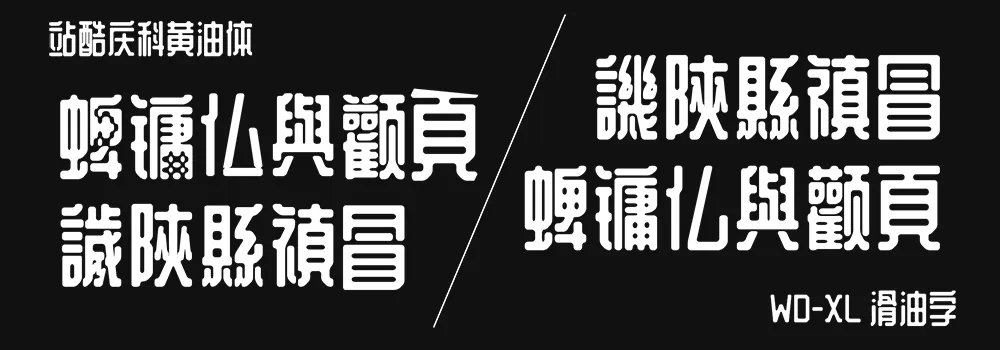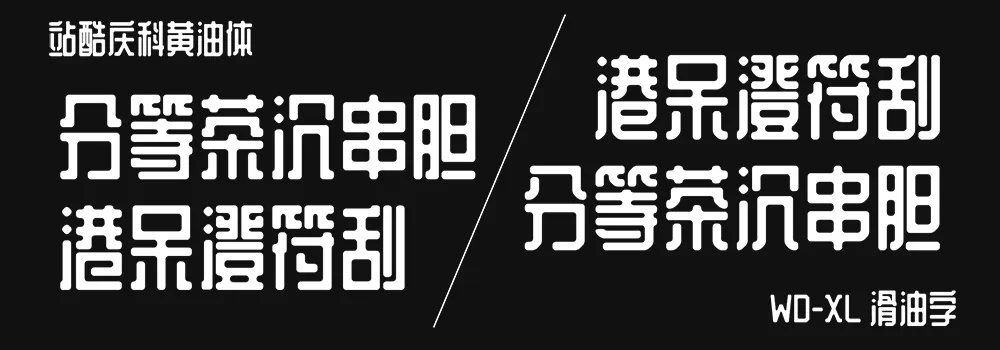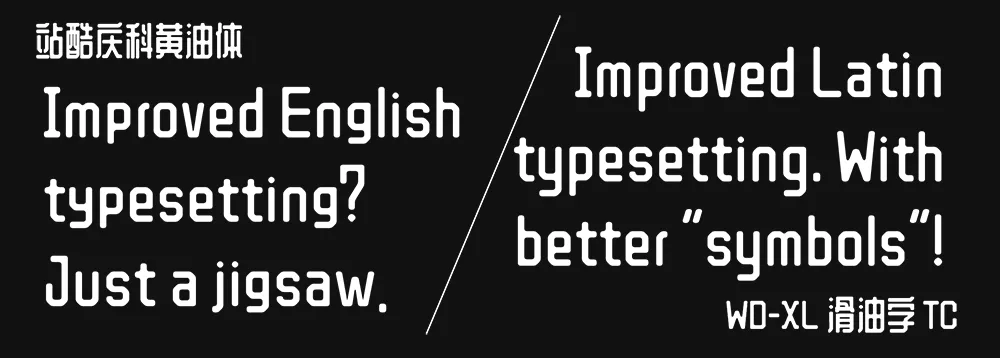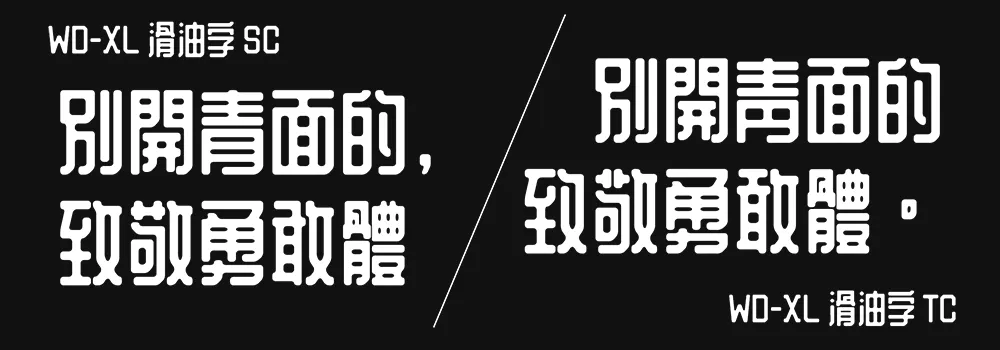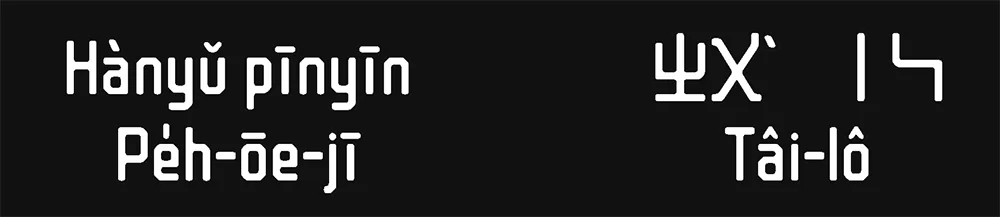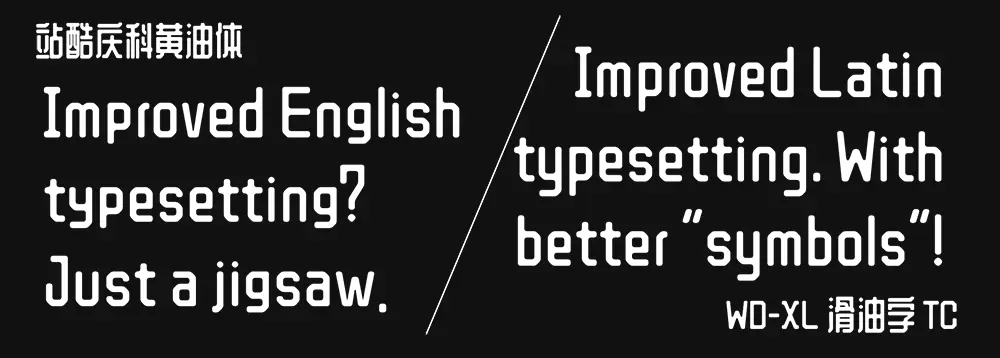
WD-XL 滑油字是在站酷慶科黃油體的基礎上為繁體(正體)中文進行常用字補字擴充,讓其能夠適配繁體(正體)中文環境,並且也補全標準中文字體所需的標點符號和功能。目前本字體支援簡體中文、繁體(正體)中文、臺語、客語、粵語的常用字,也支援白話字和臺羅拼音,日常排版使用絕無問題。
WD-XL 滑油字 是基於 站酷慶科黃油體 的字體進行繁體字補字,並且修整了標點符號及增加了中文排版所需要的符號(如漢語拼音及注音符號)。此外,本字體也改進了原字體的許多問題:
但是如果詳細查看,部分漢字其實並沒有 45° 右下斜角。本字體 1.100 版已經統一了此特徵,讓全部漢字視覺效果一致:
WD-XL 滑油字 的西文部分也經過檢查修整,確保其更適合西文排版。
原字體已經數年未更新。WD-XL 滑油字 除了修改問題以外,也聆聽了繁體中文排版界的需求,為繁體中文排版進行了修改增刪,製作了 WD-XL 黃油體 TC 版本。TC 版依據更適合印刷的傳承字形進行參考及修改以匹配原字體風格。
WD-XL 滑油字 還製作了漢語拼音、注音符號、白話字、臺羅拼音的符號呢!你可以用這個字體來製作專業排版了!
未來 WD-XL 滑油字 將會嘗試更多 OpenType 功能(主要於西文排版),敬請期待!